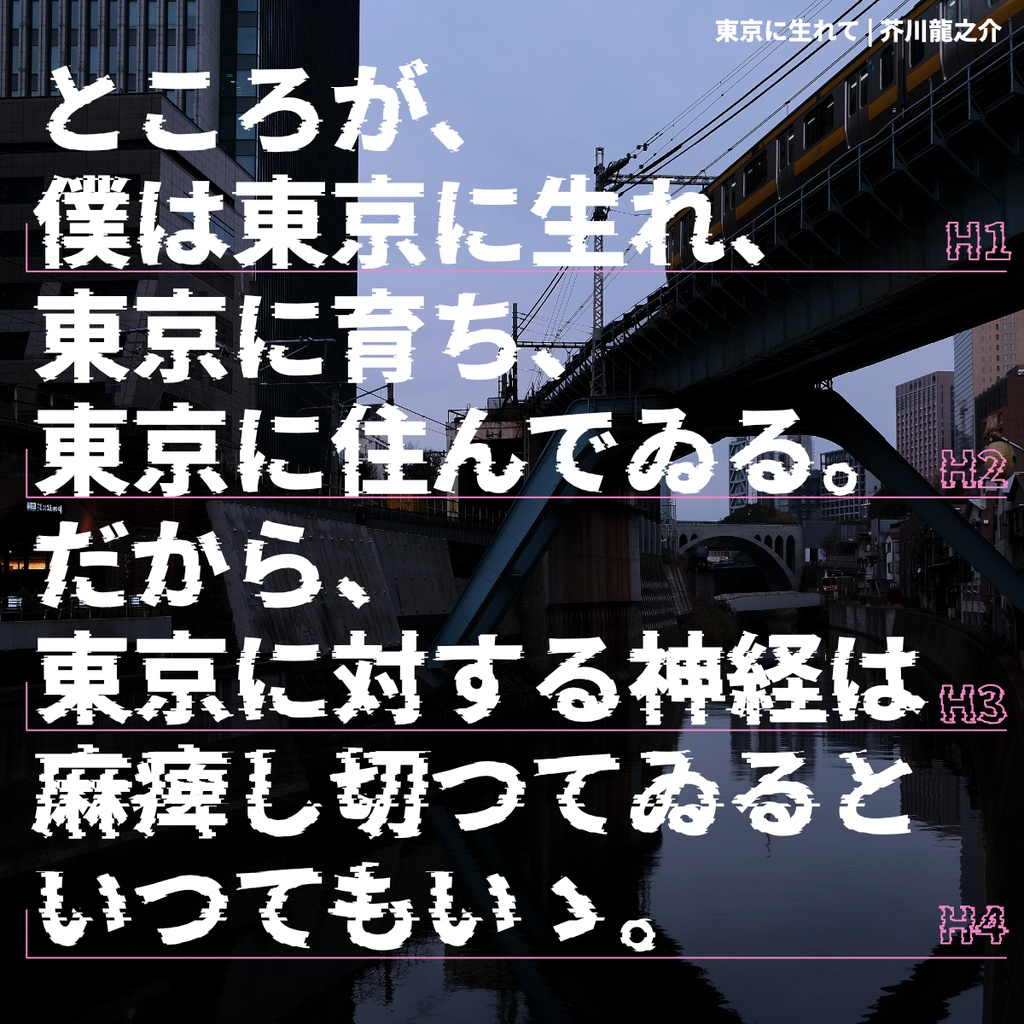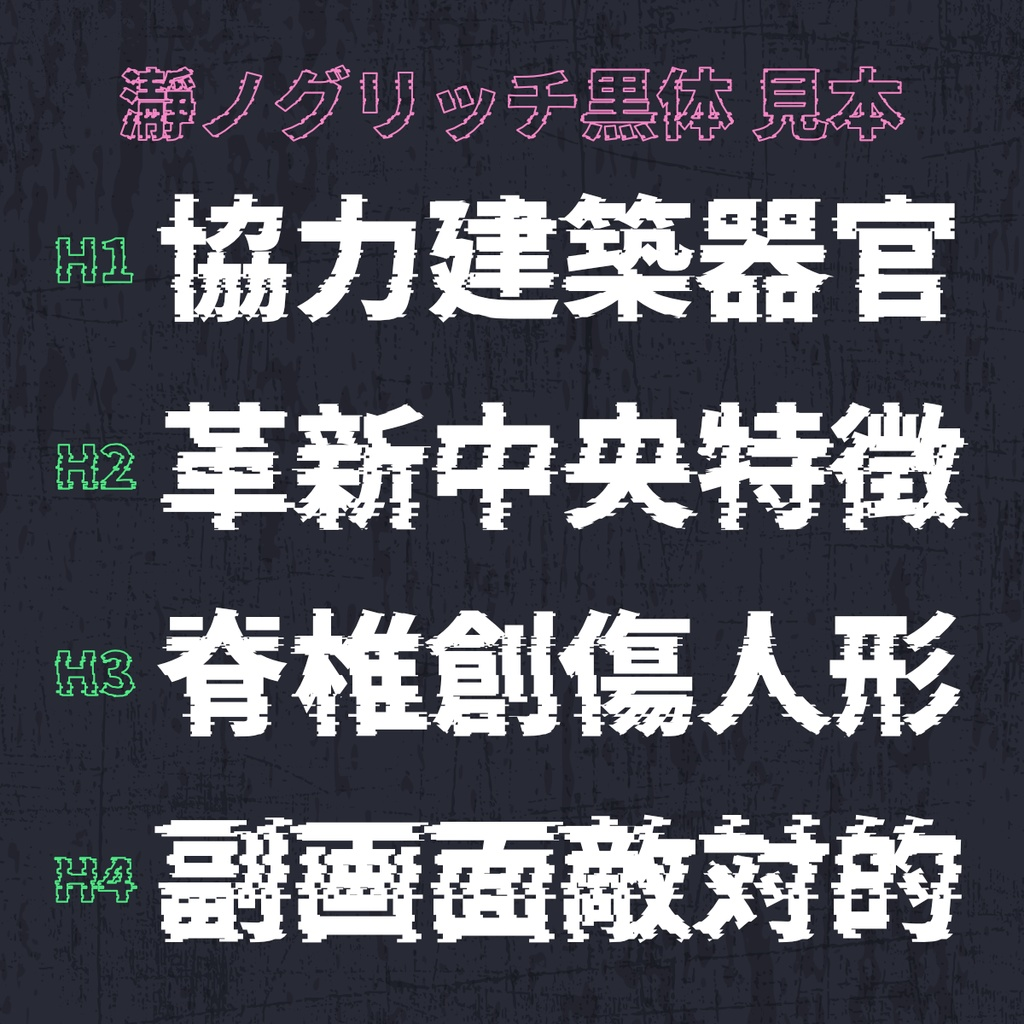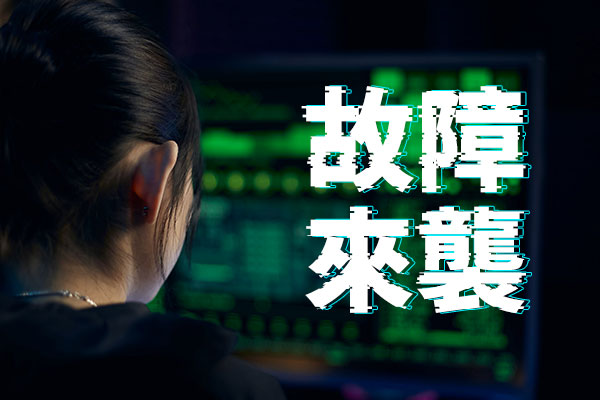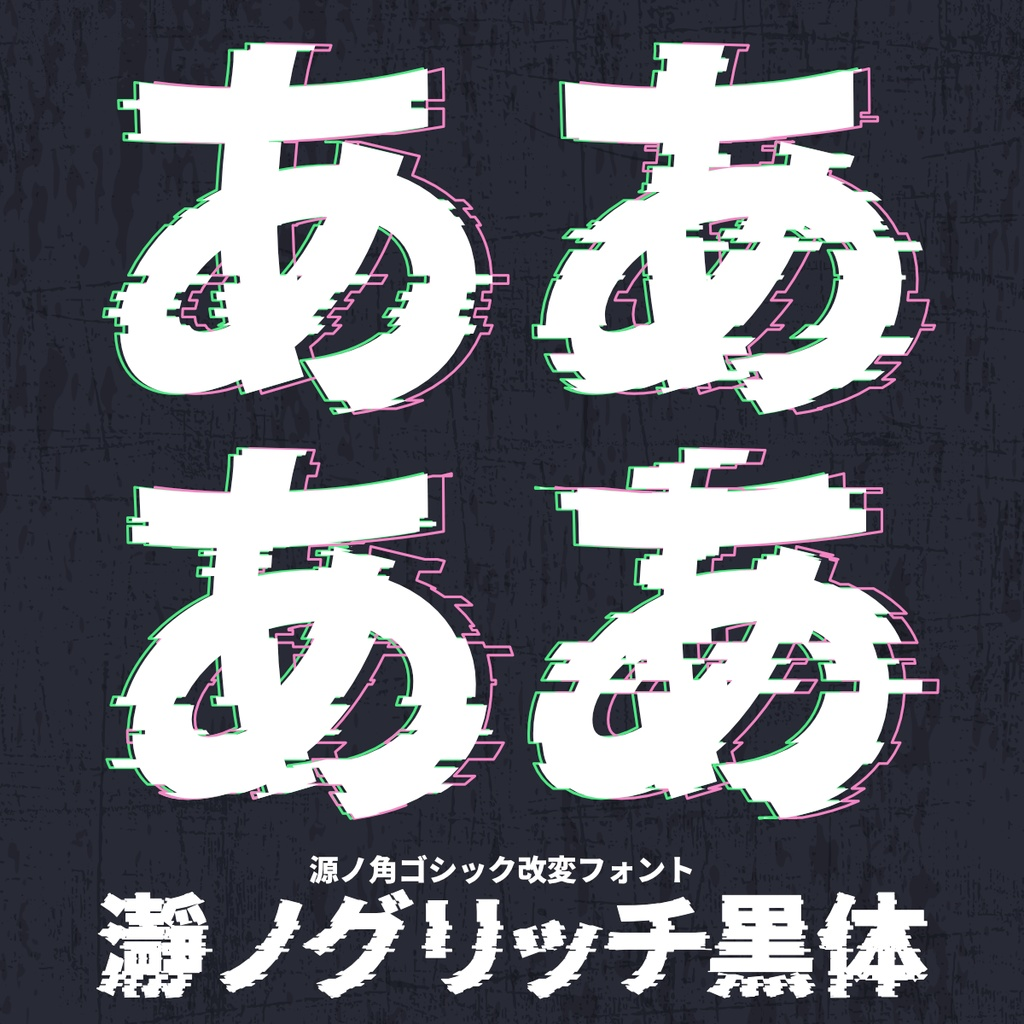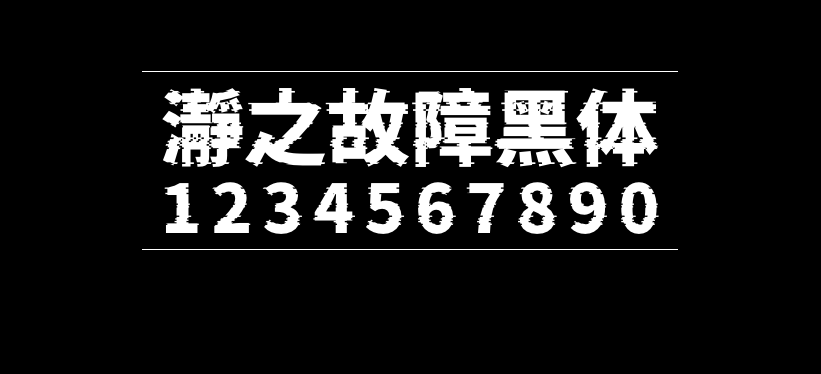
瀞之故障黑体
瀞之故障黑体(瀞ノグリッチ黒体 、 Torono Glitch Sans)是日本网友RAPTORTYPE基于思源黑体并进行了处理,并将其加工成具有抖音故障风效果的字体。
瀞之故障黑体包含H1/h2/h3/h4四个版本,由于瀞之故障黑体是日本网友制作的,并未针对简体中文进行特殊适配,所以本字体的简体中文字符存在部分缺字现象(常用字是支持的)。而繁体中文字符则支持得挺不错的,基本不缺字。